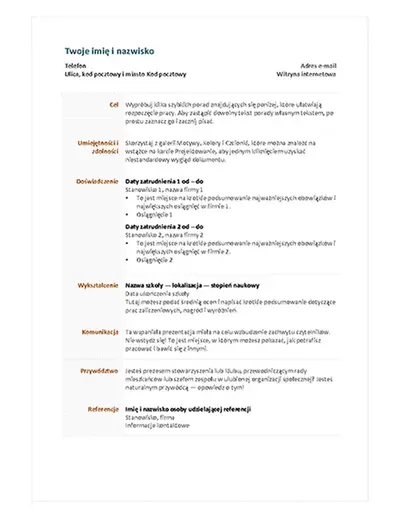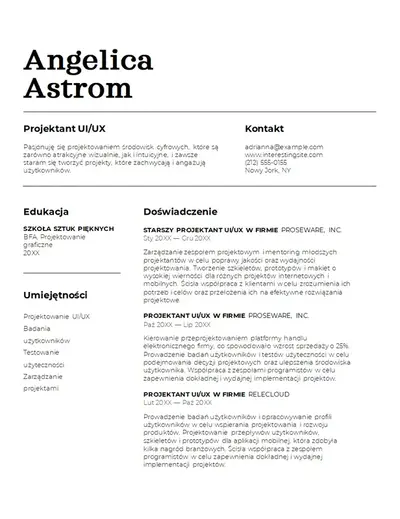
Wybór odpowiedniej czcionki do życiorysu jest jednym z najskuteczniejszych sposobów zrobienia silnego pierwszego wrażenia. Czcionki mogą wyrażać wiarygodność i osobowość, wspierać profesjonalizm i dopracowywać życiorys tak, aby odzwierciedlał dbałość o szczegóły.
Rozpocznij tworzenie dobrze zaprojektowanego życiorysu, korzystając z praktycznych porad dotyczących wyboru odpowiednich stylów i rozmiarów czcionek. Dowiedz się, jak utworzyć przejrzystą hierarchię czcionek, spójnie stosować formatowanie i utworzyć dopracowany życiorys w Microsoft Word.
Sześć najlepszych czcionek CV do każdego podania o pracę
Najlepsza czcionka życiorysu nie tylko dobrze wygląda na stronie. Wybór czcionki wpływa na sposób odczytywania, klasyfikowania i zapamiętywania życiorysu. Oto najlepsze profesjonalnie wyglądające czcionki, idealne do napisania CV, wszystkie dostępne w programie Microsoft Word.
1. Czcionka Calibri
Calibri to nowoczesna czcionka bezszeryfowa, która stała się złotym standardem korporacyjnym. Prosty w odbiorze, Calibri emanuje profesjonalizmem i autorytetem. Dzięki odważnym i lekkim stylom tę bezszeryfową czcionkę można łatwo dostosować do każdego wrażenia. Doskonale nadaje się do karier takich jak prawo, finanse i opieka zdrowotna, Calibri pasuje do każdej roli, w której priorytetem jest czysty, profesjonalny wygląd.
2. Czcionka Garamond
Garamond to klasyczna czcionka szeryfowa, która sprawdza się w profesjonalnych publikacjach i formalnych dokumentach. Czcionka jest łatwa do odczytania przy mniejszych rozmiarach, co nadaje życiorysowi autorytatywny i wyrafinowany wygląd. Garamond jest dobrym wyborem na stanowiska akademickie, wydawnicze, prawnicze i kierownicze, gdzie ceniona jest tradycyjna, wysoce wiarygodna prezentacja.
3. Czcionka Montserrat
Montserrat nadaje życiorysowi czysty, przystępny wygląd. Montserrat, krój pisma przeznaczony do reklam drukowanych i miejskich znaków drogowych, w naturalny sposób pasuje do życiorysów w dziedzinach kreatywnych, wellness i nieruchomościach. Ta czcionka bezszeryfowa jest odważna w dotyku, a jednocześnie niezwykle przejrzysta i łatwa do skanowania.
4. Czcionka Candara
Candara to subtelnie stylowa opcja, która wygląda na dopracowaną, ale nie jest zbyt formalna. Łatwa do odczytania dzięki charakterystycznemu stylowi, ta czcionka pasuje do życiorysów zawierających mniej tekstu, takich jak łączy format życiorysu , który szczególnie dobrze sprawdza się w przypadku stanowisk związanych ze stażem, oprogramowaniem i IT.
5. Czcionka Cambria
Cambria to tradycyjna, wyważona czcionka szeryfowa, która reprezentuje niezawodność i profesjonalizm. Zaprojektowany dla Łatwe czytanie na ekranie (opens in a new tab) w małych rozmiarach tekstu, Cambria to wyrafinowana opcja, która pasuje do każdego życiorysu. Ta czcionka szeryfowa sprawdza się w rolach kierowniczych, kadrowych i kierowniczych oraz stanowi zgrabne rozwiązanie do życiorystów inżynierskich i architektonicznych, ponieważ jej konstrukcja obsługuje symbole matematyczne i naukowe.
6. Czcionka Aptos
Aptos to czcionka domyślna w programie Microsoft Word i na platformie Microsoft 365, która łączy nowoczesny styl z dużą czytelnością, aby utworzyć przejrzyste CV umożliwiające zeskanowanie. Zaprojektowane z myślą o czytelności na nowoczesnych ekranach o cieplejszym, bardziej neutralnym tonie, Aptos (opens in a new tab) to elastyczna czcionka bezszeryfowa, która dostosowuje się do nagłówków i tekstu podstawowego. Ta współczesna czcionka doskonale nadaje się do zastosowań technologicznych, opieki zdrowotnej i zarządzania.
7. Czcionka Arial
Arial to przejrzysta, prosta czcionka bezszeryfowa, która nadaje życiorysowi profesjonalny, łatwy do zeskanowania wygląd. Jego elastyczność sprawia, że jest to praktyczny wybór w przypadku życiorysów na różnych stanowiskach i etapach kariery, udostępnianych zarówno w formie cyfrowej, jak i drukowanej. Ta schludna i spójna czcionka jest szczególnie zgodna z aplikacjami korporacyjnymi, klienckimi i biznesowymi.
Jak wybrać profesjonalną czcionkę do życiorysu
Po wybraniu krótkiej listy odpowiednich czcionek następnym krokiem jest znalezienie odpowiedniego dopasowania dla podanie o pracę. Wybór odpowiedniej czcionki w zależności od stanowiska i poziomu stażu pracy wymaga zrozumienia niuansów kulturowych i zawodowych każdego sektora pracy, a także wrażenia, jakie musi wywrzeć na potencjalnych pracodawcach. Oto kilka wskazówek ułatwiających wybranie najlepszej czcionki.
Weź pod uwagę rolę i poziom stanowiska
Różne stanowiska i poziomy stażu pracy mogą wpływać na to, jak kreatywny lub formalny powinien być projekt życiorysu i czcionka. Weź pod uwagę poziom starszeństwa roli, poziom podstawowy, średni lub senior, ponieważ od tego zależy swoboda twórcza wybrana czcionka.
Na przykład: Calibri może nadać życiorysowi czysty, profesjonalny wygląd w przypadku stanowiska kierowniczego, podczas gdy Montserrat może nadać bardziej współczesny charakter rolom w dziedzinach kreatywnych.
- Jak edytować czcionkę życiorysu i rozmiar czcionki w programie Word?
Otwórz życiorys w programie Word, zaznacz tekst do zaktualizowania i użyj listy rozwijanej czcionki na karcie Narzędzia główne, aby wybrać nową czcionkę. Dostosuj rozmiar tekstu, używając pola rozmiaru czcionki obok niego. Aby zaktualizować wszystkie nagłówki lub tekst podstawowy jednocześnie, kliknij prawym przyciskiem myszy odpowiedni styl w galerii stylów i wybierz polecenie modyfikuj. Zmiana jest stosowana automatycznie w całym dokumencie. Aby poznać więcej sposobów edytowania i formatowania dokumentów w programie Word, zobacz Edytor dokumentów.